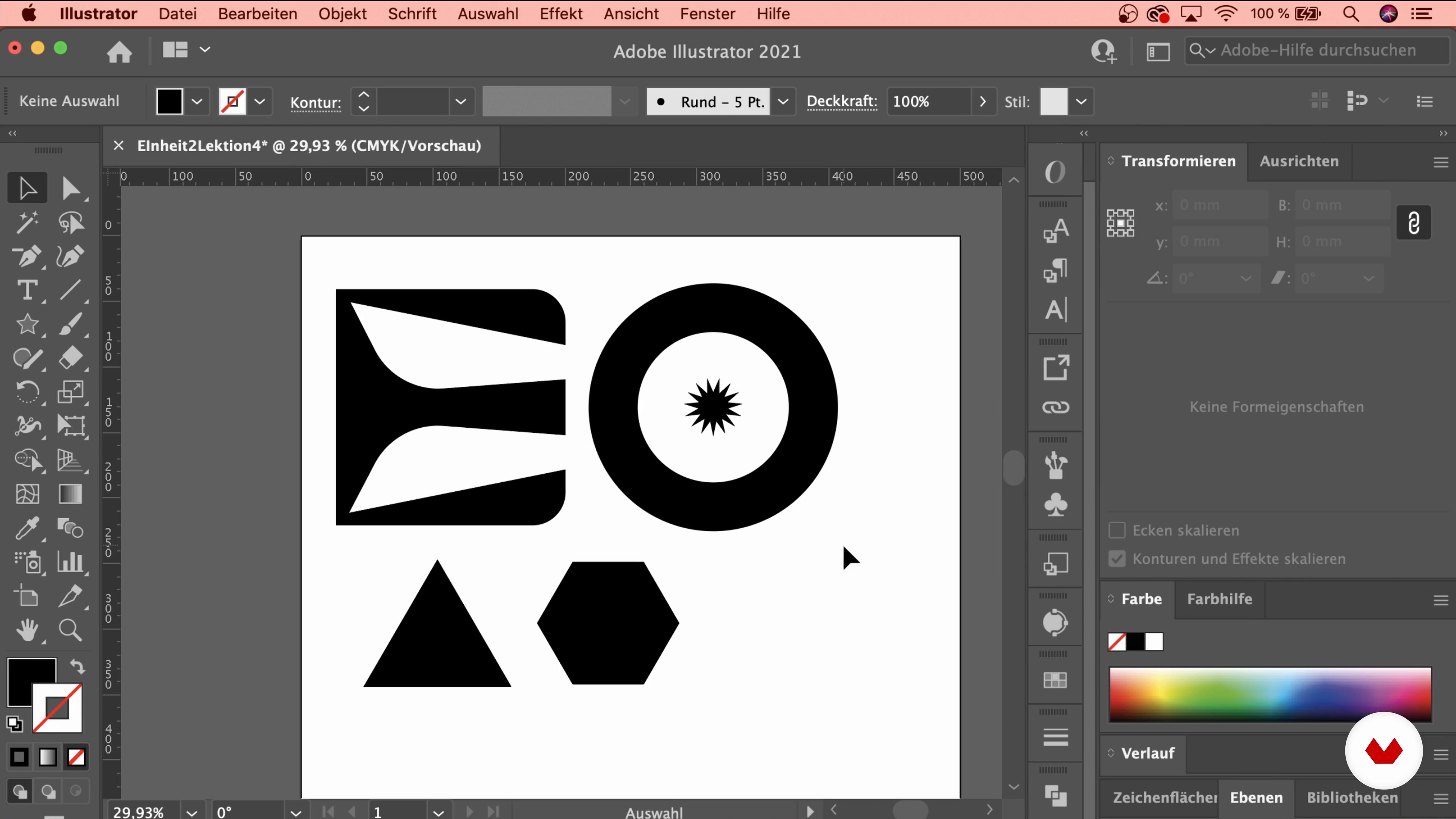
Typografisches Posterdesign mit Illustrator
Mit dem Raster arbeiten
Über die Videolektion: Mit dem Raster arbeiten
“In dieser Lektion fangen wir an, mit Adobe Illustrator zu arbeiten. Wir übertragen unser analoges Raster ins Digitale und gestalten einige Buchstaben.”
In dieser Videolektion behandelt Steffen Wagner das Thema: Mit dem Raster arbeiten, das Teil dieses Domestika-Onlinekurses ist: Typografisches Posterdesign mit Illustrator. Entwickle ein Gefühl für Typografie und Komposition und gestalte ein kreatives Poster mit versteckter Botschaft.
Partielle Transkription des Videos
“Mit dem Raster arbeiten Jetzt, wo ich dir die Grundlagen des typografischen Designs nähergebracht habe, können wir in dieser Lektion damit beginnen, in Illustrator zu arbeiten und das erste Raster anzulegen. Das ist das Programm Adobe Illustrator. Wir werden ein neues Dokument erstellen mit den Abmaßen 500 mal 700 Millimeter, dass ist ein gängiges Posterformat, von daher arbeiten wir direkt in diesen Dimensionen. So, hier wird der Name des Dokumentes eingetragen. Nun Einheit 2. Lektion 4. Erstellen. Und bekommen so unser Dokument in den richtigen Abmaßen. So, es geht los, wir möchten unser ...”
Zusammenfassung des Kurses: Typografisches Posterdesign mit Illustrator